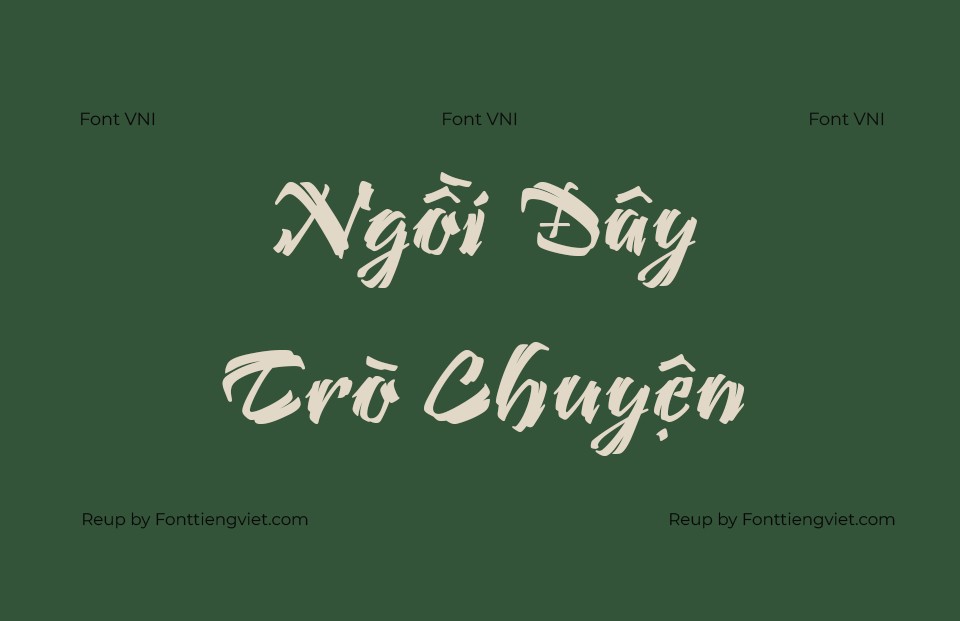
Font Việt hoá VNI 27 Bendigo
Font Việt hoá VNI 27 Bendigo – Bộ Font Chữ Nghệ Thuật Cho Thiết Kế Ấn Tượng
Giới thiệu về Font Việt hoá VNI 27 Bendigo
Trong thế giới đồ họa hiện đại việc lựa chọn một Font Miễn Phí chất lượng đóng vai trò quyết định đến tính thẩm mỹ của sản phẩm. Font Việt hoá VNI 27 Bendigo là một cái tên nổi bật trong hệ thống phông chữ trang trí tại Việt Nam. Với những đường nét cách điệu độc đáo và mềm mại bộ phông này mang lại cảm giác cổ điển xen lẫn hiện đại. Đây là lựa chọn lý tưởng cho các bạn học sinh sinh viên muốn làm mới bài thuyết trình hoặc thiết kế thiệp chúc mừng đầy sáng tạo.
Đặc điểm nổi bật của Font Việt hoá VNI 27 Bendigo
Đặc trưng lớn nhất của Font Việt hoá VNI 27 Bendigo chính là cấu trúc ký tự thanh thoát nhưng vẫn giữ được sự chắc chắn. Font chữ này đã được tối ưu hóa bảng mã VNI truyền thống giúp người dùng dễ dàng gõ tiếng Việt có dấu mà không bị lỗi hiển thị. Dù bạn đang sử dụng các phần mềm văn phòng cơ bản hay các công cụ thiết kế chuyên nghiệp thì bộ font này vẫn luôn đảm bảo tính ổn định và sắc nét trên mọi khung hình.
Ứng dụng thực tế của Font Việt hoá VNI 27 Bendigo trong đời sống
Bởi tính ứng dụng cao Font Việt hoá VNI 27 Bendigo thường xuyên xuất hiện trong các dự án in ấn như bìa sách tiêu đề báo tường hay các loại banner sự kiện trường học. Khả năng gây ấn tượng thị giác mạnh mẽ giúp người xem dễ dàng ghi nhớ nội dung thông điệp. Việc kết hợp font này với các tông màu trầm sẽ tạo nên vẻ đẹp sang trọng và chuyên nghiệp cho tác phẩm của bạn.
Kết luận về bộ font chữ độc đáo